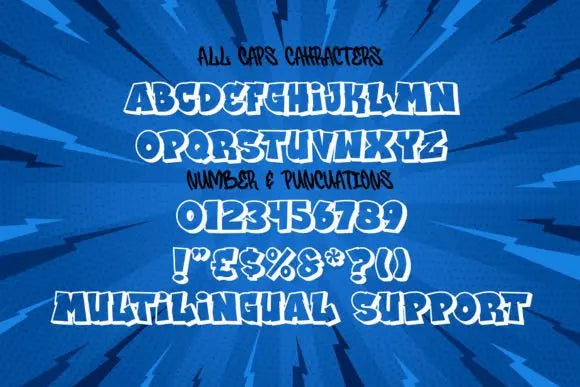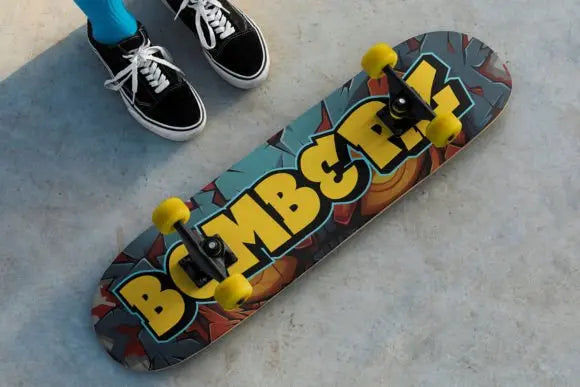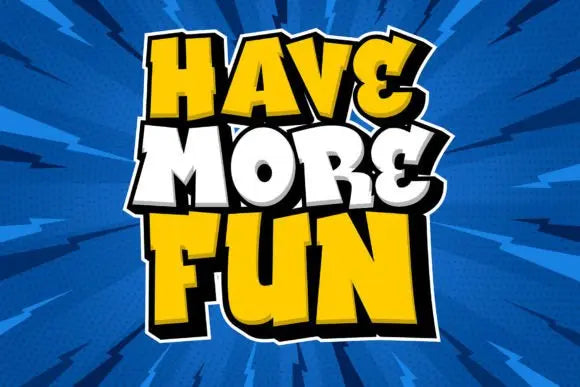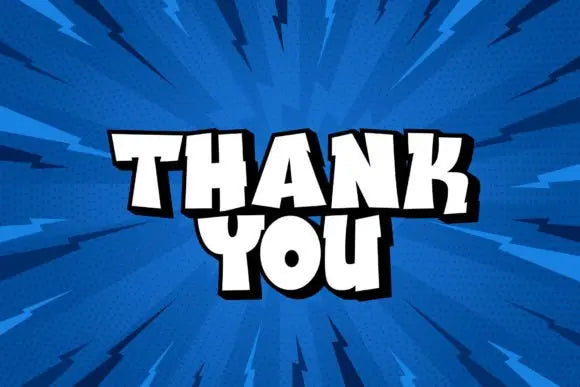
Fuente Waosh
“Waosh” es una tipografía de cómic 3D robusta y vivaz, que rezuma un dinamismo lúdico que anima cualquier diseño. Al poseer una composición en capas, crea un dramático impacto 3D, generando profundidad y estimulando la curiosidad visual en su trabajo. Ideal para cómics extravagantes, carteles divertidos, literatura infantil y cualquier proyecto que necesite una tipografía llena de entusiasmo juvenil.
"Waosh" amplifica tus diseños con su encanto estimulante y fascinante. Con "Waosh" a tu disposición, tus diseños rebosarán de entusiasmo juvenil. Perfecta para cómics extravagantes, literatura infantil o cualquier proyecto que necesite un toque de diversión, esta fuente robusta y dinámica añade profundidad e interés visual a tu trabajo.
Su composición en capas crea un espectacular impacto 3D que cautivará y atraerá a su audiencia. Deje que "Waosh" amplifique sus diseños con su encanto estimulante y fascinante.